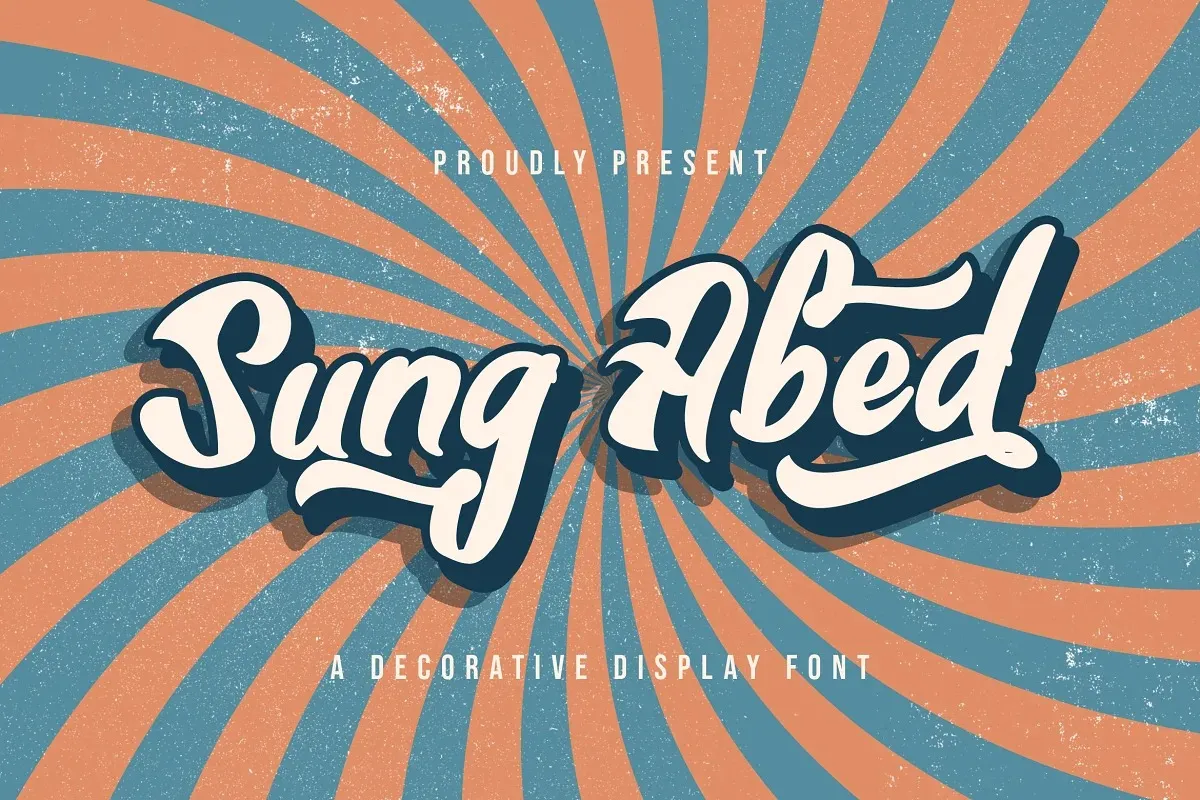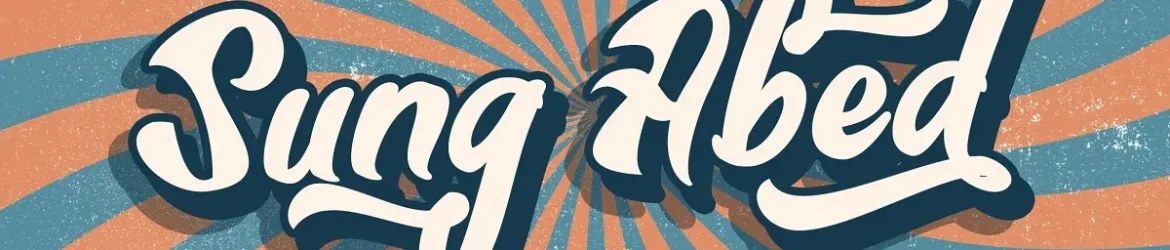
A fonte Sung Abed é uma obra de arte criada pelo designer StringLabs com base em letras entrelaçadas à mão. Essa escolha temos por ser notável para diversos projetos gráficos, especialmente aqueles que requerem um toque autêntico e sofisticado. Perfeita tanto para criações como logotipos ou rótulos de embalagens, quanto para identidade corporativa e merchandising, a Sung Abed traz uma textura suave e elegante à sua próxima iniciativa gráfica. Sua elegância faz dela um recurso indispensável para aqueles que desejam agregar um toque diferenciado a qualquer projeto visual em seu portfólio.